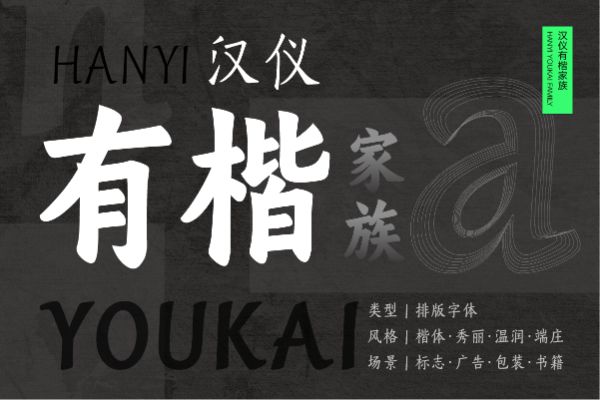
汉仪有楷 35W
一款为应用而生的楷书排版家族字体。习欧楷之险绝严谨,取其工整森然,兼顾欧楷韵味与排版应用。字体气象庄严,笔画方圆兼施,刚柔并济,体现欧楷的中和之美。 汉仪有楷家族,从35到95共有7个字重,细体中宫紧凑,显隽逸清朗、险峻挺拔、谨严瘦劲;粗体中宫稍放,显厚重潇洒、风骨内存、丰润饱满。汉仪有楷以工整大气的面貌适应不同的应用场景,发挥其优秀的应用效果。